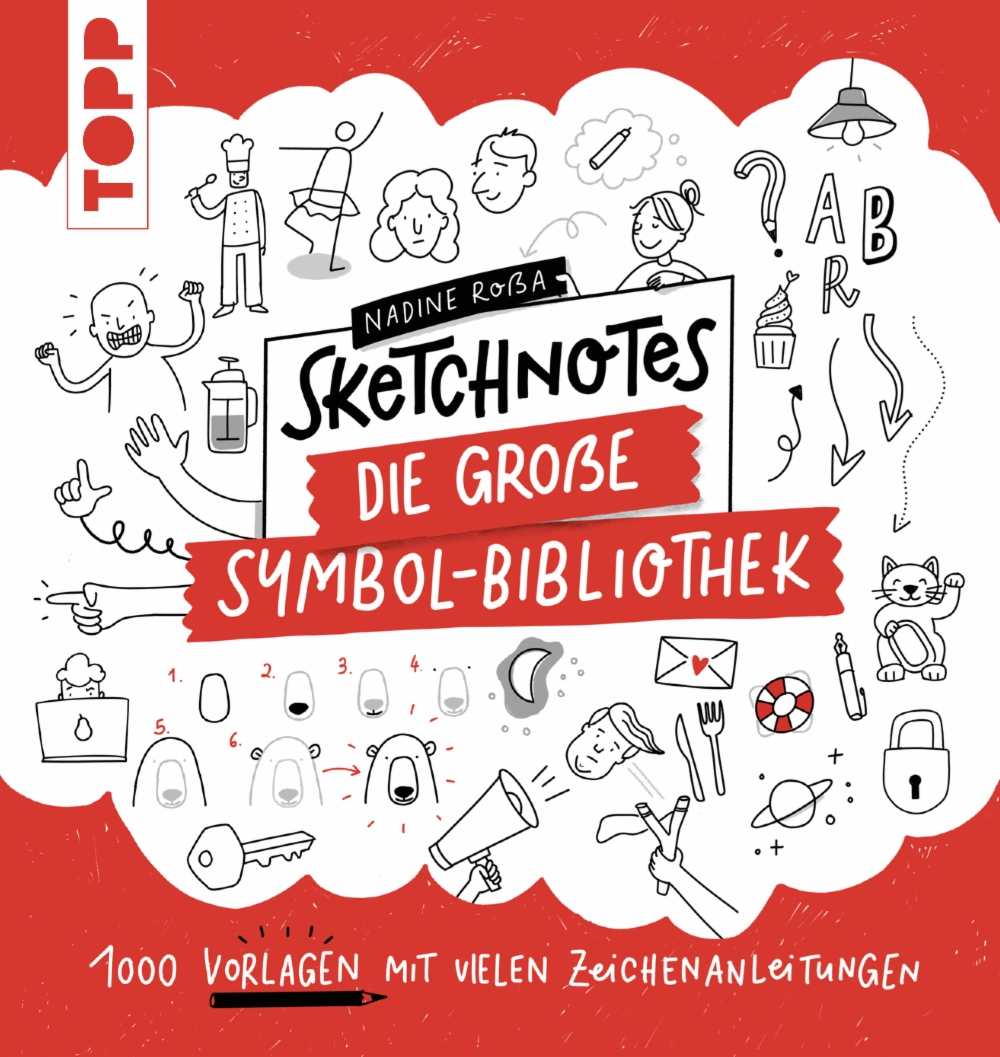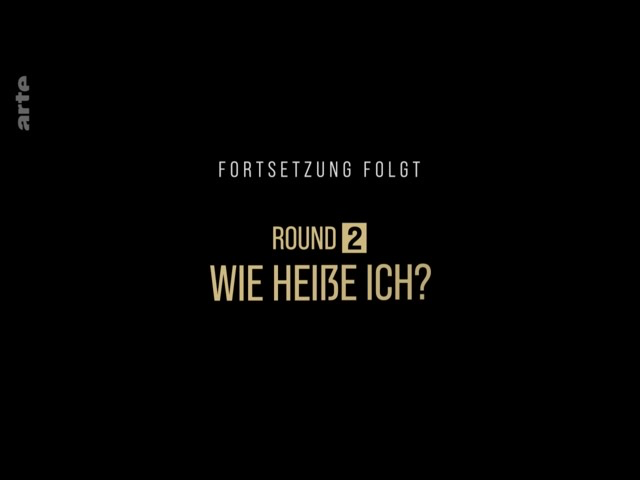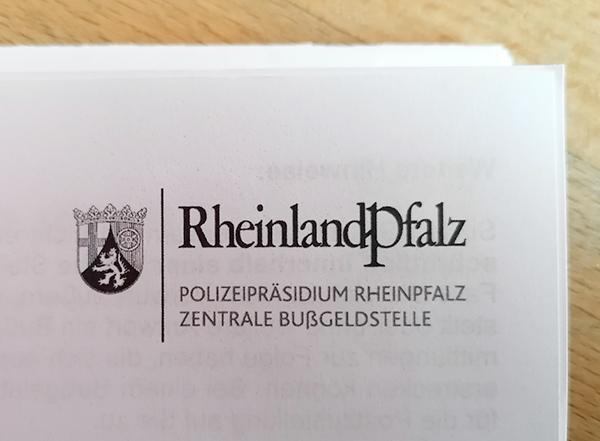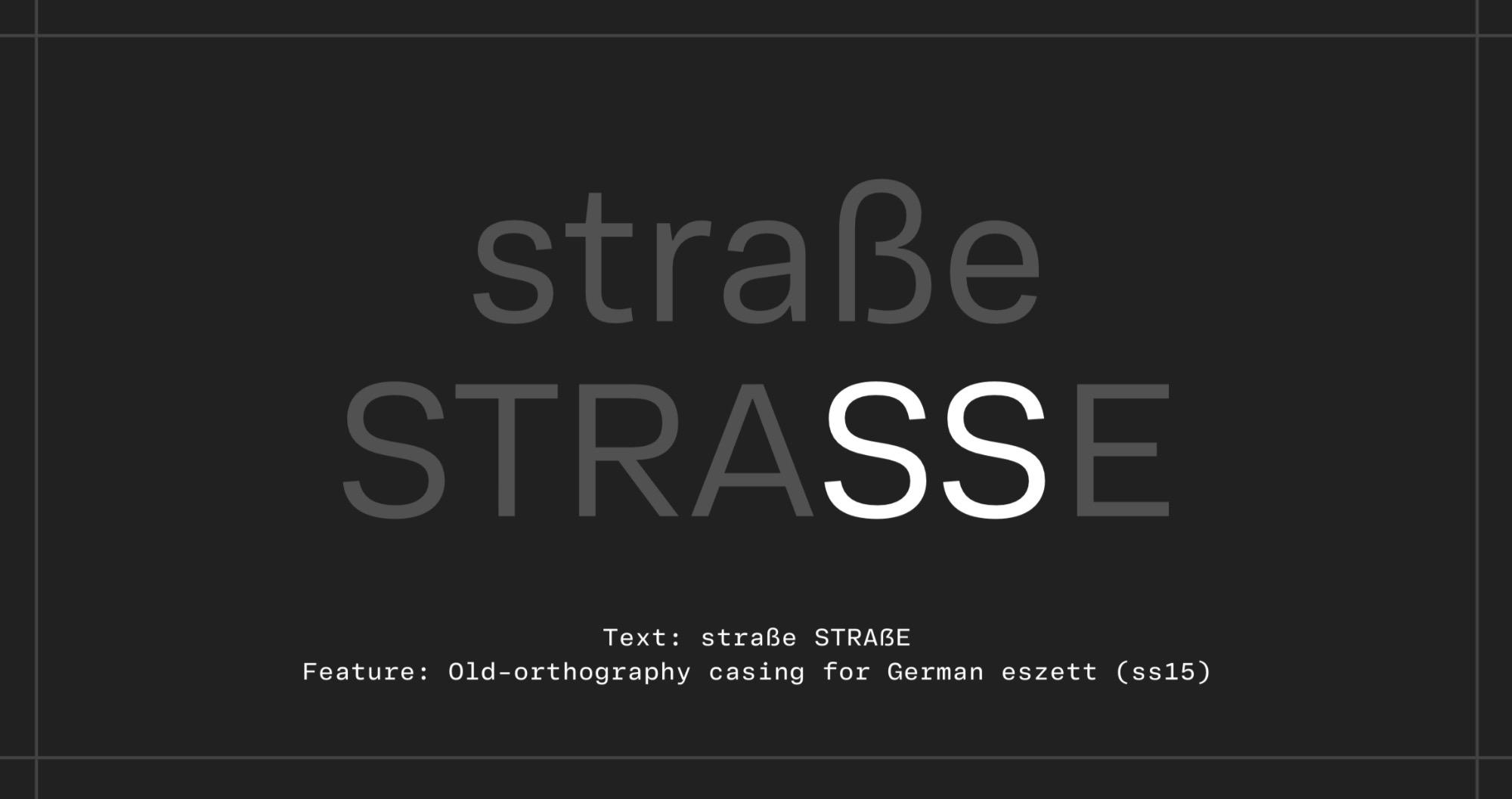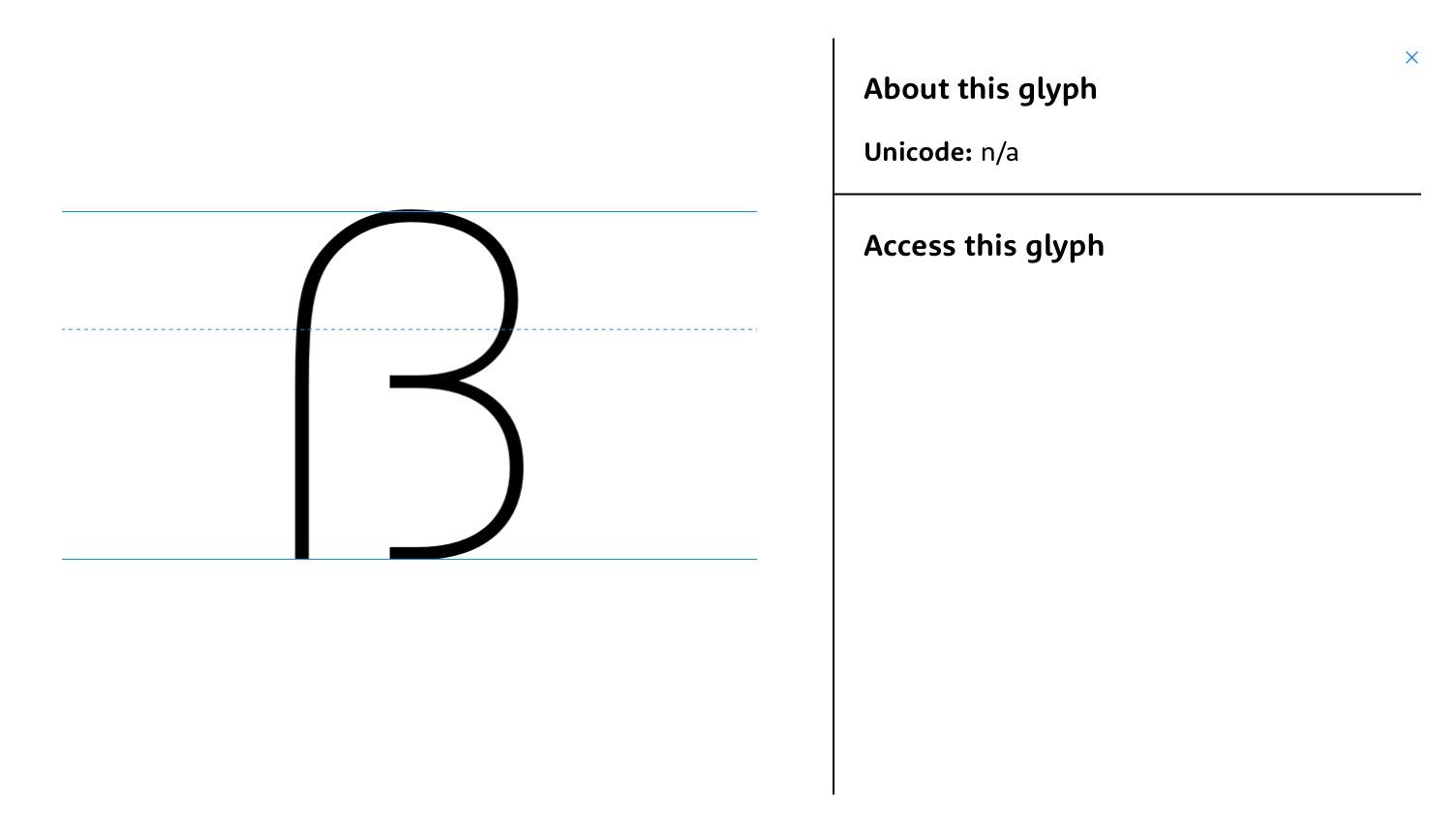
Jiddisch, im Lateinischen Schriftsystem, hat anscheinend eine Anzahl Wörter, die mit Eszett anfangen. Könnt ihr euch vorstellen, wie fantastisch ein Zier-Eszett sein würde? :rockon:
Jiddisch.
a ßach – viel(e)
ßejder – Ordnung, Reihenfolge
ßmach – Grundlage
ßojcher – Händler
ßchojre – Ware
ßakóne – Gefahr
ßibe – Grund, Ursache
ßod – Geheimnis
ßojne – Feind
ßam – Gift
ßimche – Freude, Fest
ßof – Ende
ßof-kl-ßóf – letztendlich
ßtam – schlecht- hin, einfach
ßejchl – Verstand
ßimen – Zeichen, Merkmal
ßtire – Widerspruch
ßofek – Zweifel
ßwiwe – Umgebung, Milieu
Typedrawers lässt grüßen, hmm? ;-)
Aus der Diskussion dort, aber auch schon vorher, hatte ich den Eindruck, dass es sich bei der lateinisch-schriftlichen Version wirklich nur um eine Umschrift handelt, die die Aussprache veranschaulichen soll.
Es wäre spannend, herauszufinden, ob es wirklich solcherart gedruckte Texte gibt.
Aber ja, so ein Zier-Eszett, das wäre schon was.
Es wäre spannend, herauszufinden, ob es wirklich solcherart gedruckte Texte gibt.
Ich bekam Post. Jene, die mit einem Verwarngeld verbunden ist. 10 km zu schnell, 20 Euro. Ich denke darüber nach 40 Euro zu überweisen, damit sich das Land Rheinland-Pfalz ein großes ẞ leisten kann.
Das sehe ich zum ersten Mal: Eine Schrift mit Versal-ẞ bewirbt nicht, dass es diese Glyphe hat, sondern dass es auch die »old-orthography« Methode der Ersetzung durch Doppel-S unterstützt. Was ist das: ein Plädoyer für die Beibehaltung der SS-Verlegenheitsschreibung oder aber ein Hinweis, dass das Versal-ẞ nichts besonderes mehr ist? Hmmm?!
dass das Versal-ẞ nichts besonderes mehr ist
… sondern Standard, genau – so lese ich das zumindest und finde es amüsant und irgendwie auch lässig. Vielleicht sind sie ihrer Zeit voraus? ;-)
… damit sich das Land Rheinland-Pfalz ein großes ẞ leisten kann.
Was soll denen ein Versal-ß nutzen, wenn sie sich nicht einmal ein Versal-P leisten können?
Jaja, der Schriftzug im Logo meines Bundeslandes ist schon speziell. Die Serifen wirken schwerfällig, der Strichstärkenunterschied irgendwie zufällig. Die Spationierung ist wohl Symbol für bürokratische Engstirnigkeit und die Punzen von e mussten so hoch, und die von a so tief, dass dazwischen die Beamtenlaufbahn Platz findet.  Das Pfalz-Versal-P ist in den Keller gerutscht. Soll dies ein Zeichen für das Niveau der Pfälzer sein?
Auf der Homepage von RLP gibt es eine Datei, die das Wappen erklärt.  OK, sie ist von 1999. Das gilt aber weniger als Entschuldigung, denn als zusätzlicher Anklagepunkt.
Die Hauptstadt von RLP ist Mainz, der Geburtsstadt Gutenbergs.
Wie tragisch dass dann auch noch die ITC Garamond für den Schriftzug herhalten musste. An sich eine brauchbare Schrift, hat aber wenig mit Garamond zu tun. Mit den beiden nicht so richtig harmonierenden Schriftzügen hinkt das Ganze zwischen falsch verstandene Tradition und Moderne.
Ich werde aus den neuen FontFont-DINs nicht so richtig schlau: Zwar habe ich eine Form entdeckt, welche man unter Umständen als Versaleszett deuten könnte, jedoch lässt sich diese in der Myfonts-Vorschau nicht mit der entsprechenden Tastatur-Belegung ansteuern. Stattdessen erscheint das Doppel-S. Was ist da los?
Und wie kommt es, dass die Paneuropean kein Griechisch kann, die Pro hingegen schon?
Wo hast du gesehen, dass die FF DIN Paneuropean kein Griechisch kann? Ist wahrscheinlich ein Fehler auf (einer) der Website(s). Sag gerne Bescheid, dann wird der Fehler behoben.